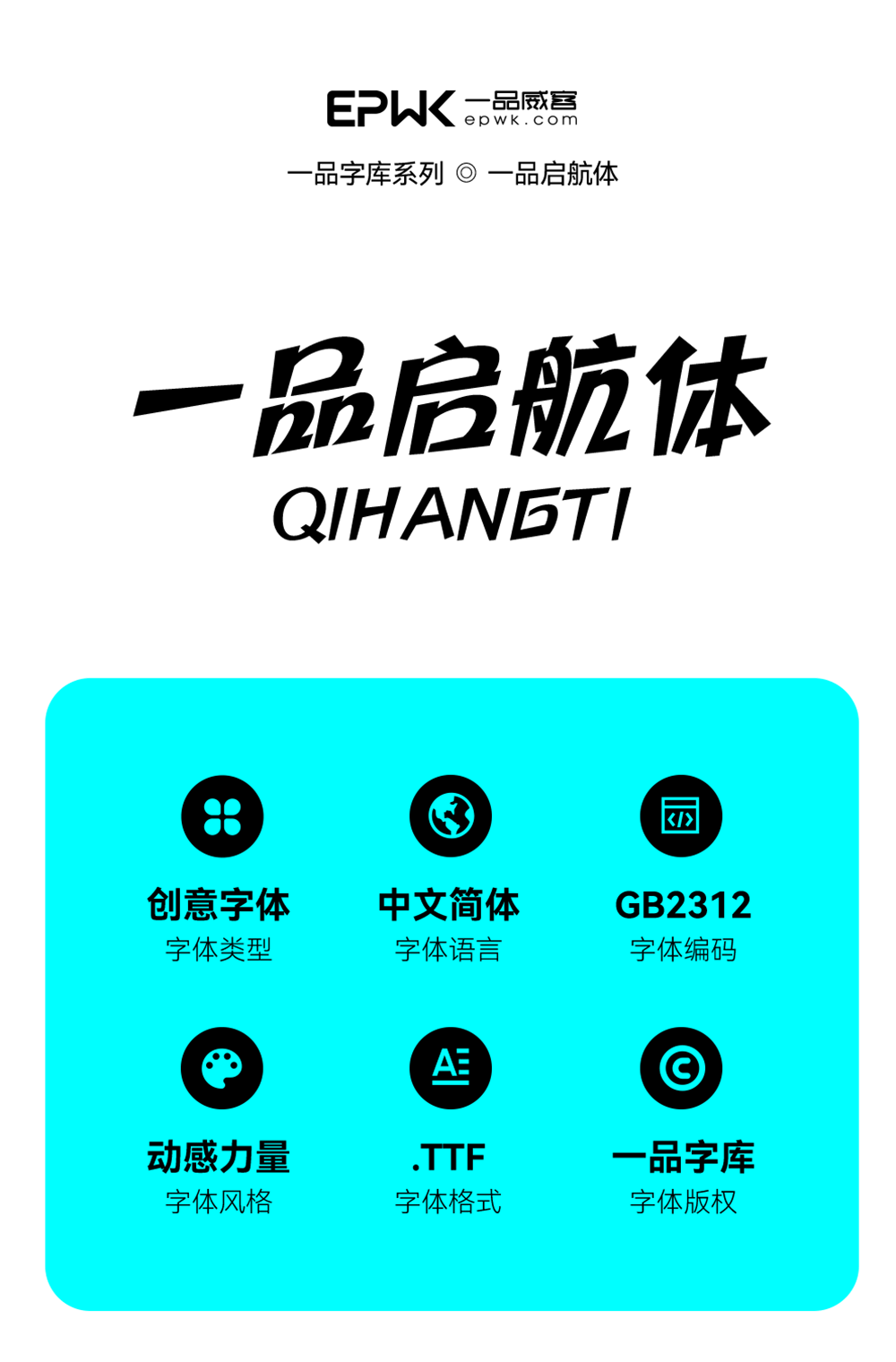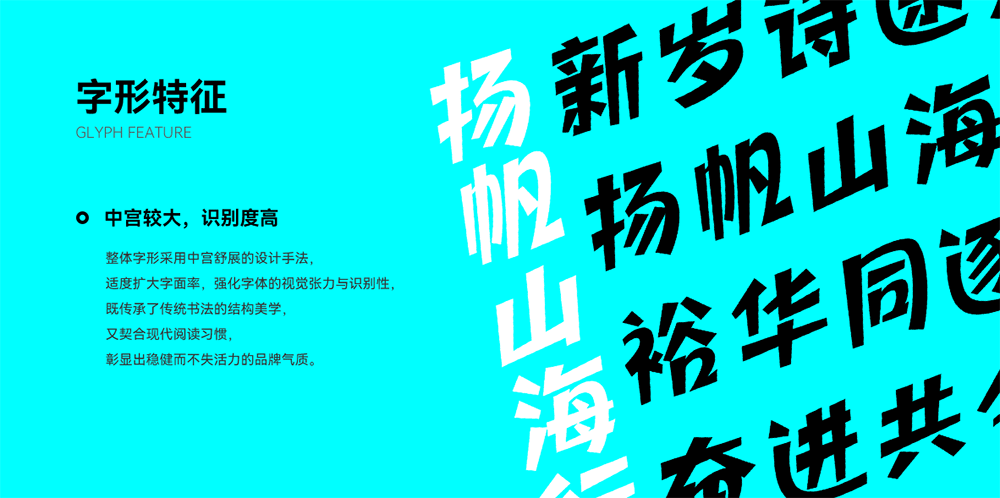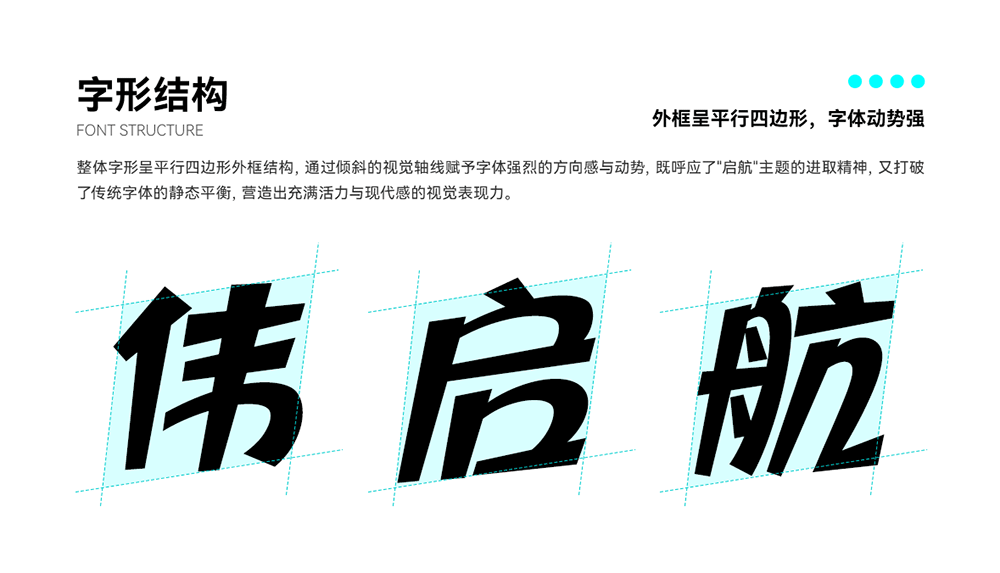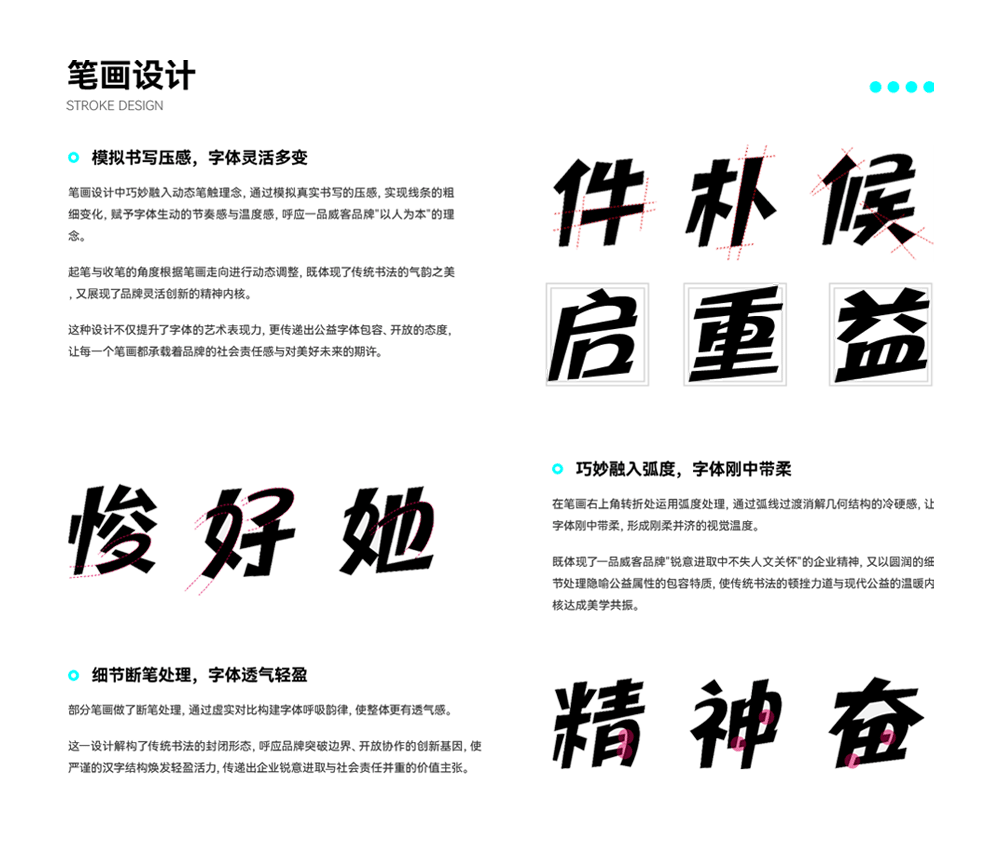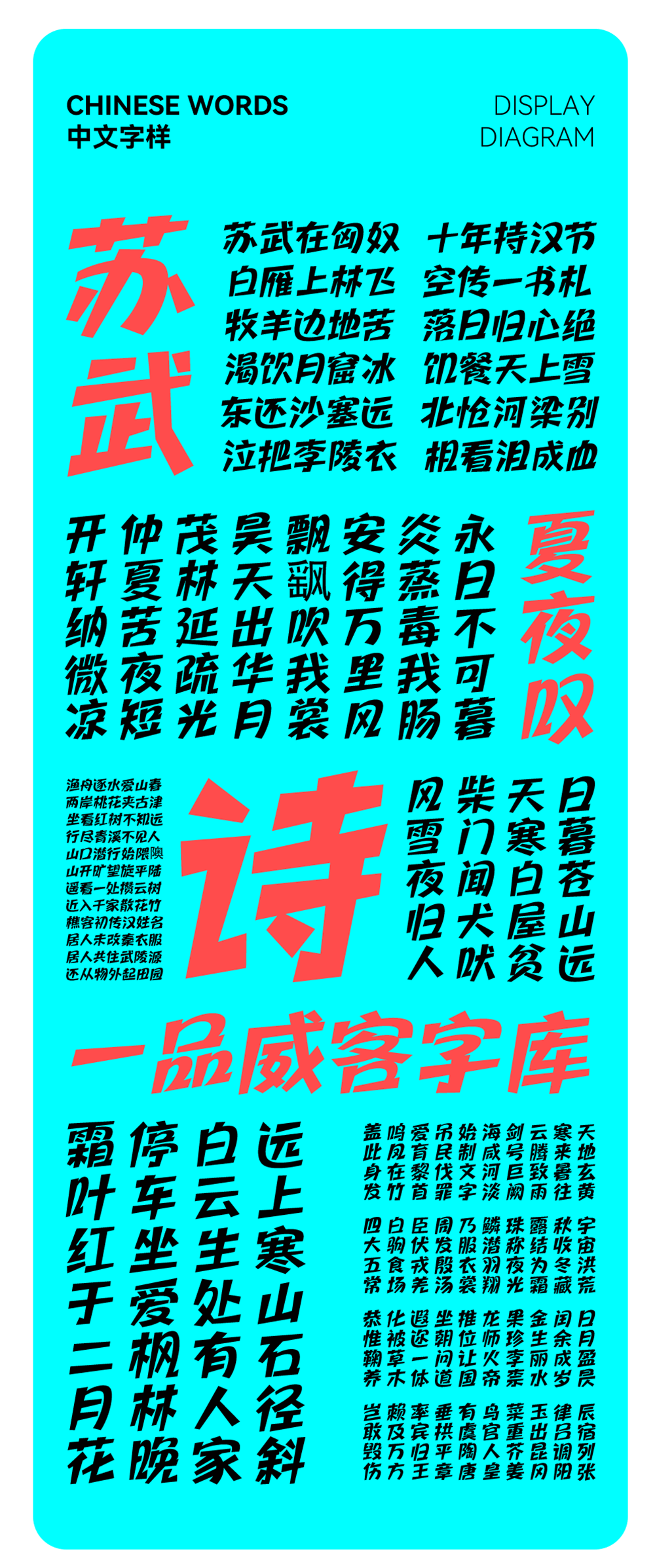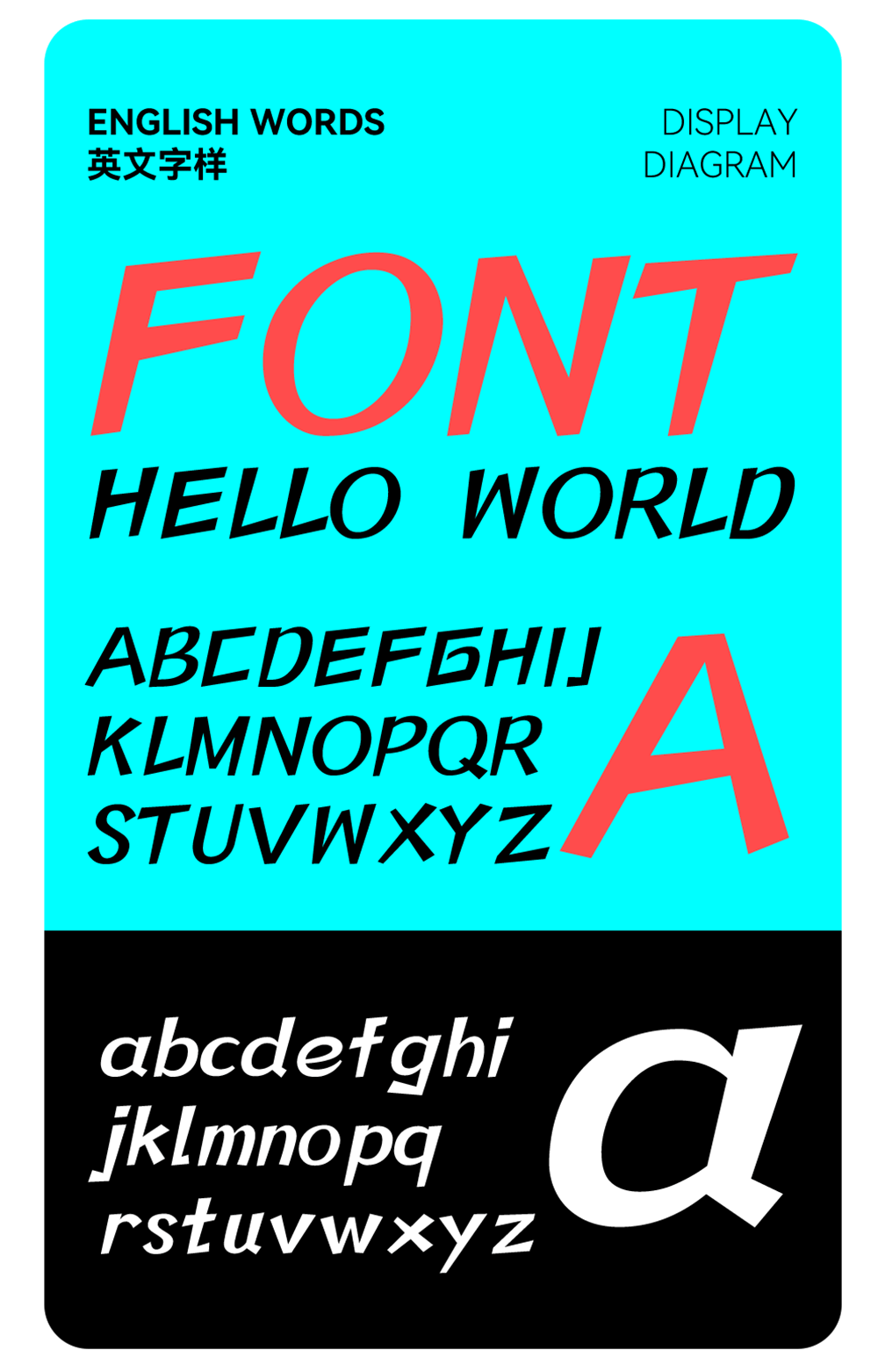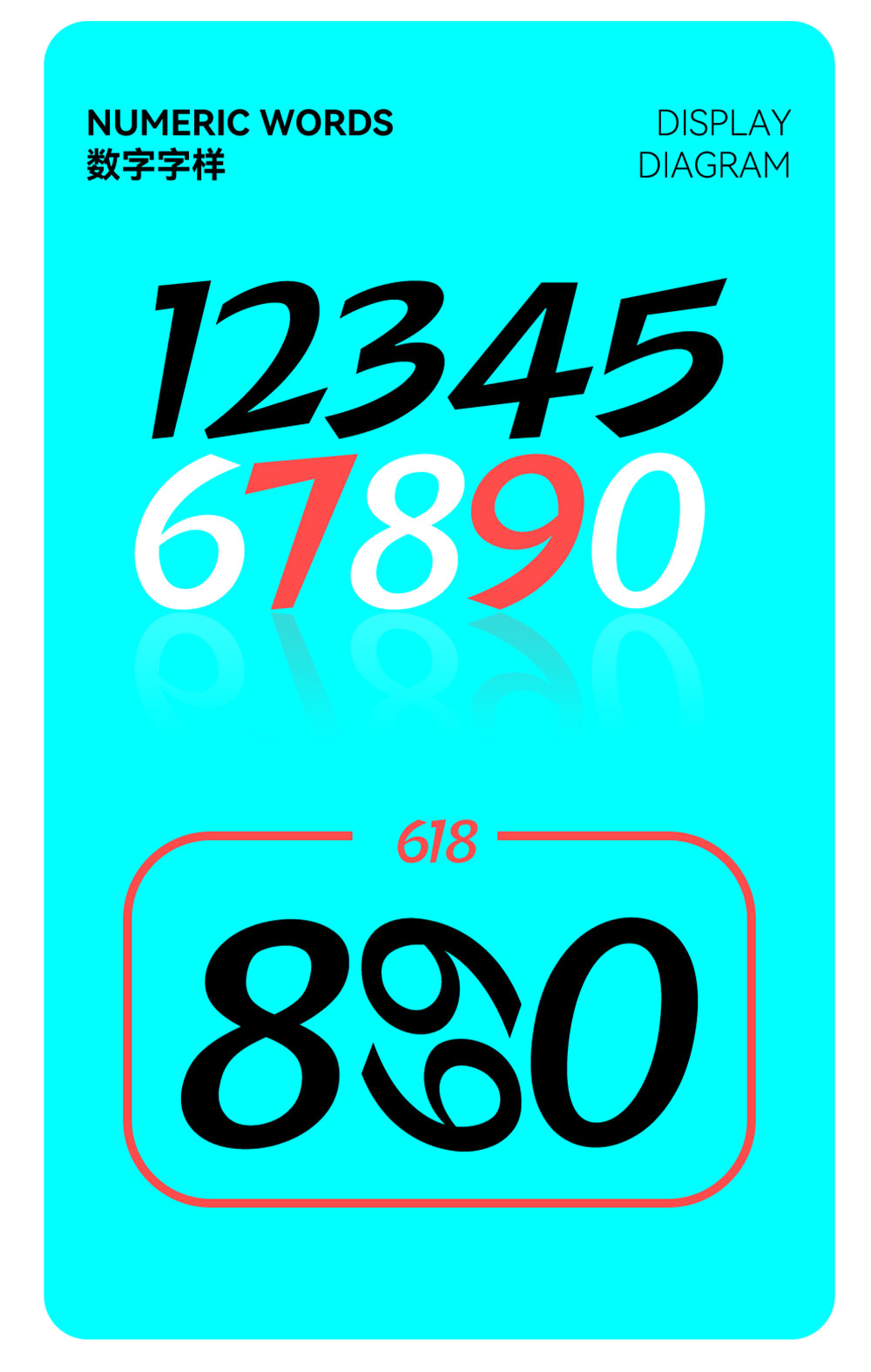
美国时间 2025 年 2 月 6 日,一品威客在美国纳斯达克证券交易所挂牌上市,股票代码为 EPWK,系国内首家赴美上市的数智化创意设计交易服务电商平台。这是梦想的里程碑,也是新征程的起点。为纪念这一历史性时刻,我们倾情打造公益字体“一品启航体”,以字为舟,承载梦想,扬帆远航。
“一品启航体”以中国传统书法为根基,融入现代设计美学,字形遒劲有力,笔锋昂扬向上,寓意着一品威客锐意进取、勇立潮头的企业精神。字体将免费向社会开放,用于公益事业、文化传播、商业使用等领域。我们希望,这款字体能够成为连接你我、传递正能量的桥梁,激励更多人勇敢追梦,共创美好未来。以“一品启航体”为舟,携手共进,驶向更加广阔的星辰大海!